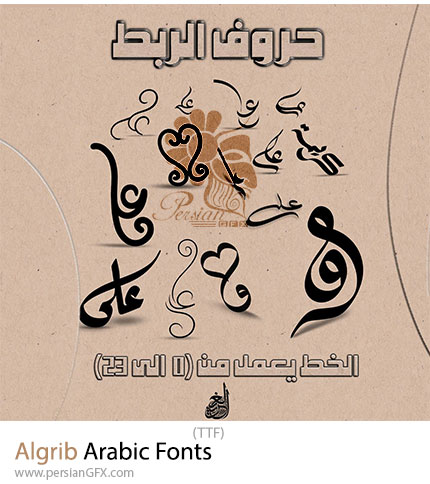
در این بخش شاهد فونت عربی الغریب می باشید که با فرمت TTF بر روی سایت برای دانلود قرار گرفته است. فونت الغریب یک فونت عربی است که طراحی زیبا و جذابی دارد و برای استفاده در پروژههای مختلف گرافیکی و طراحی مناسب است. این فونت معمولاً برای پروژههایی که به استایل مدرن یا سنتی نیاز دارند، استفاده میشود و برای طراحی پوسترها، تبلیغات، لوگوها، و محتواهای دیجیتال بسیار محبوب است. از این فونت در ترکیب با فونتهای سادهتر برای طراحی حرفهای استفاده کنید. در تایپوگرافی یا طراحیهایی که تأکید بر اصالت و زیبایی دارند، این فونت میتواند تأثیرگذار باشد.